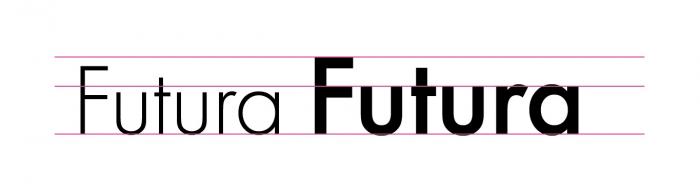
Größe der Buchstaben unterschiedlicher Schnitte
ich bin neu hier und hoffe, dass mir jemand fachkundig weiterhelfen kann: Ich nutzen die Futura in verschiedenen Schriftschnitten – über die Jahre habe ich die Schnitte einzeln nachgekauft und bin daher nun ins Grübeln gekommen: Setze ich den Medium mit dem Light-Schnitt zusammen ein (Logo) bei gleiche Schriftgröße, verfügen die Buchstaben über unterschiedliche Ober- und Mittellängen:
Meine Frage dazu: Ist das darauf zurückzuführen, dass diese von unterschiedlichen "Herstellern" stammen, oder ist das normal für die Futura. (Ich habe es z.B. mit der Frutiger verglichen… hier gleichen die Höhen auch bei unterschiedlichen Schnitten)
Würdet ihr die Höhen manuell anpassen oder so lassen?
Wenn die von verschiedenen Herstellern sind und damit verschiedene eigenständige Digitalisierungen sind ist das kein Wunder.
Wenn du sie trotzdem nebeneinander verwenden willst und InDesign benutzt, gibt es hier irgendwo ein Skript wo du bei verschiedenen Schriften die Größe per Klick anpassen kannst – an der Versalhöhe oder auch x-Höhe. Ob das passt und nicht weiter auffällt kann ich so aber nicht sagen.
Vielen Dank für deine schnelle Antwort – also kann das so nicht gewollt sein, und Ober- und Mittellängen müssen Schnittübergreifend übereinstimmen?
Müssen nicht! Wenn ein Hersteller die zusammen anbietet, damit man sie zusammen benutzen kann, ist das schon sinnvoll, wenn die vertikalen Metrics übereinstimmen. Gewollt ist der Unterschied bestimmt nicht ...
Gerade, wenn man sich eine Schriftart von verscxhiedenen Anbietern zusammenkauft muss man auch damit rechnen, dass siese beim Digitalisieren von unterschiedlichen Entwurfsgrößen ausgegangen sind. Der eine geht von den Entwürfen für die Werksatz-Schriftgröße aus, der andere benutzt eine Displaygröße als Ausgangspunkt.
Zu Zeiten, als diese Schrifen für den Bleisatz geschnitten wurden, wurde dies für jede Schriftgröße individuell gemacht, und dabei die Proportionen der Schrift auf die jeweilige Größe derart angepasst, das sie optisch in den verschiedenen Größen, und der damit verbundenen Wahrnehmungen optisch zusammenpassen wirkten. So waren sehr kleine Schriften oft etwas fetter, zarte Details wurden teils vereinfacht, kräftiger geschnitten und auch das Verhältnis von x-Höhe zu Ober- und Unterlängen leicht verstärkt. auch die Laufweiten waren dann anders. Vergrößert man eine sehr kleine Blei-Schrift auf Plakatgröße einfach linear, sehen die Buchstaben oft völlig falsch aus, ebenso käme einem eine Schrift, die für Displaygrößen geschnitten ist, auf 6 Punkte verkleinert viel zu zart vor.
Zudem nutzt der eine Digitalisierer vielleicht die echte Kegelhöhe, wärend der andere von gesetztem Text ausgeht, und so den Durchschuss in seinen digitalen, virtuellen Kegel mit einbezieht - dadurch ist die Schrift dann bei gleicher gewählter Schriftgröße etwwas kleiner.